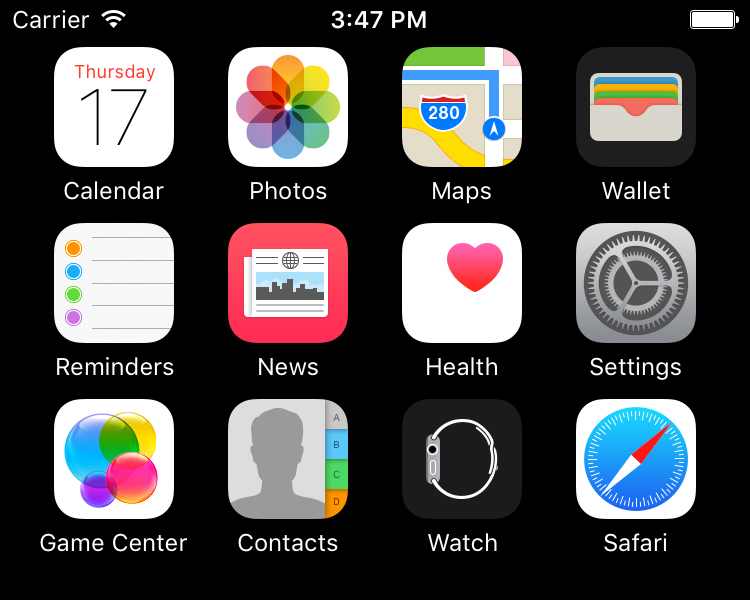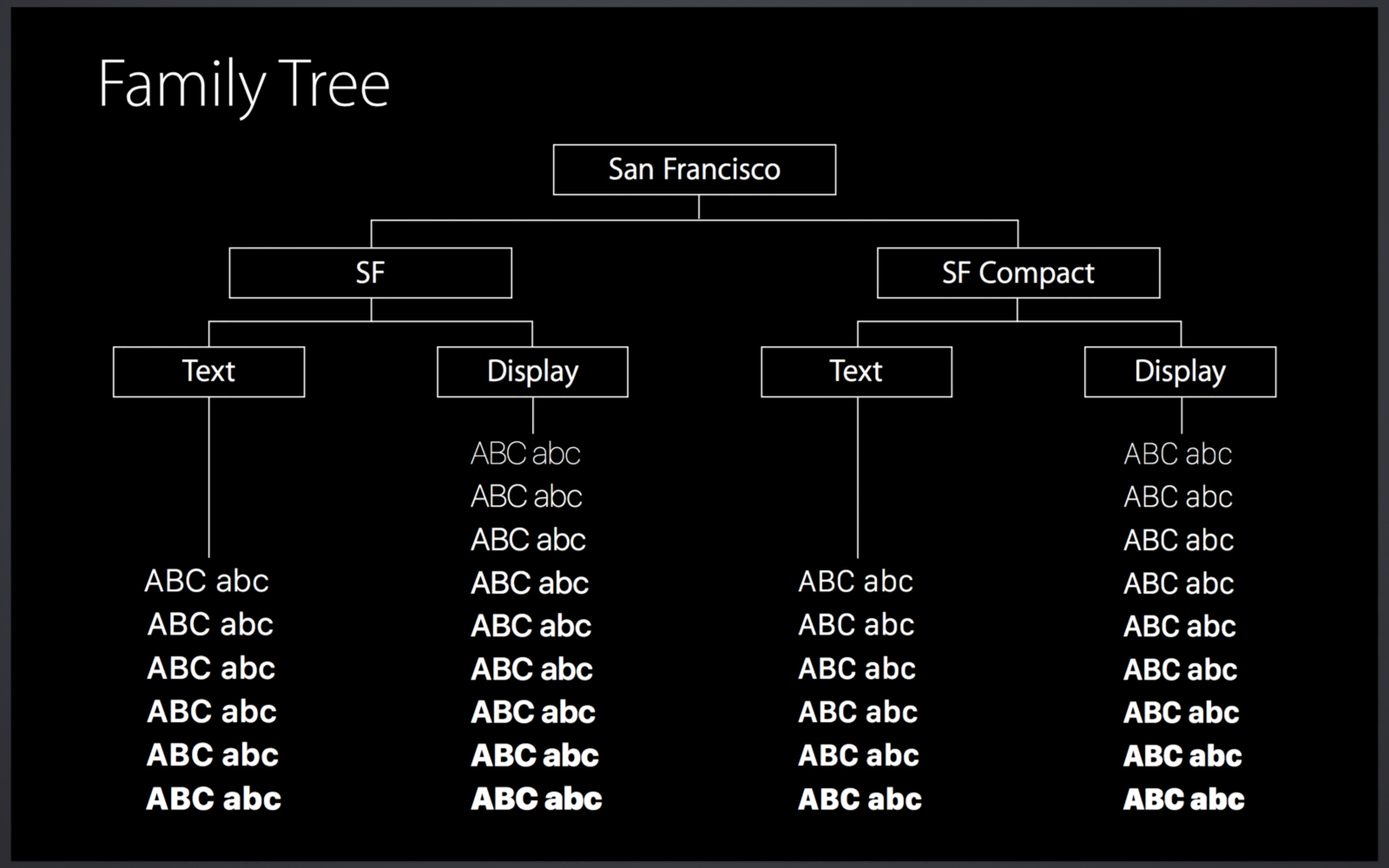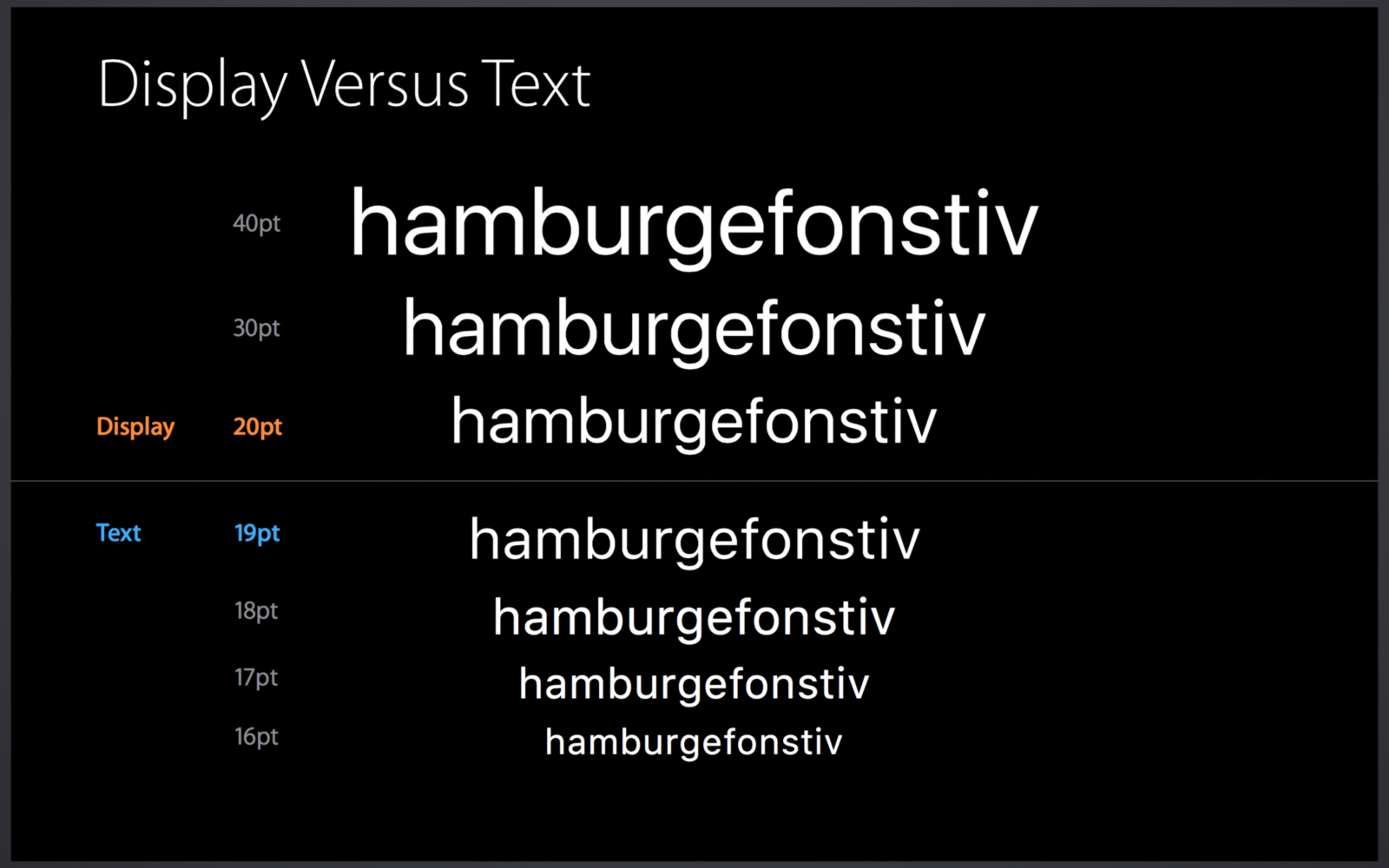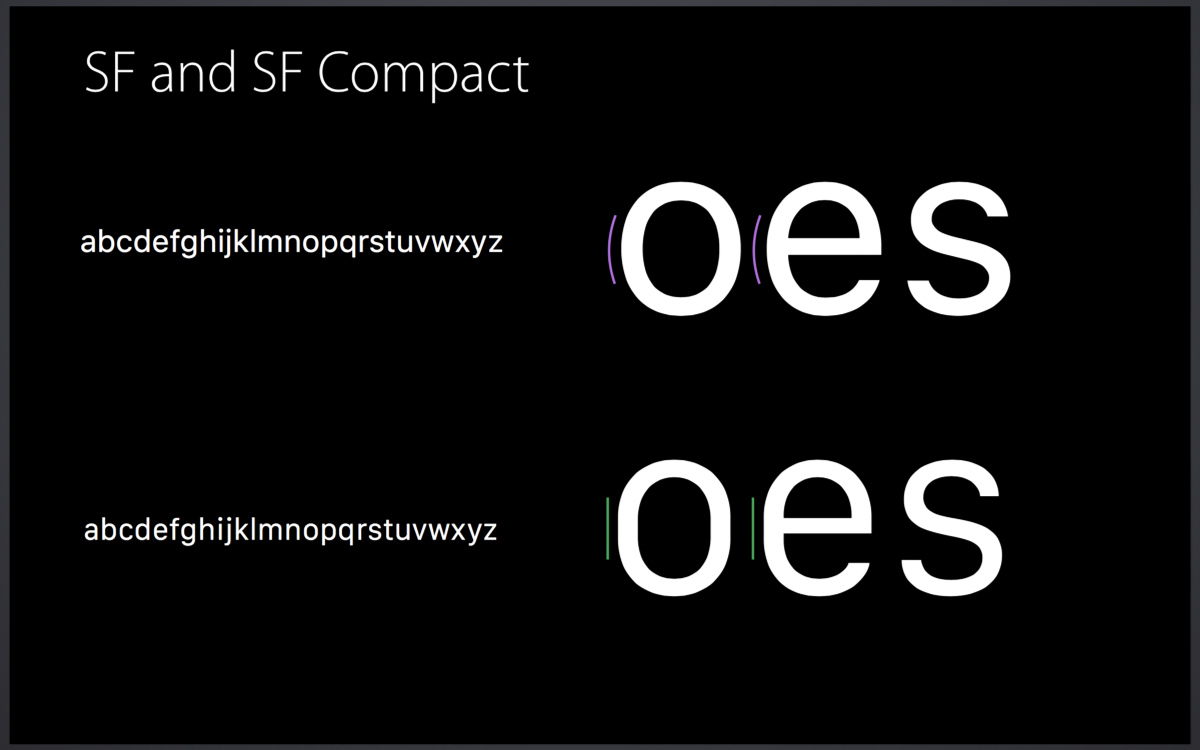
从iOS 9开始,苹果公司使用全新的San Francisco字体代替了之前的Helvetica Neue字体。目前这款全新的字体已经成为苹果各个产品平台的默认字体。
全新的San Francisco字体
Helvetica
Helvetica字体由一家瑞士公司于1957年设计,之后数字化。它历史悠久,甚至追溯到一个还没有电子设备的时代。自第一代iPhone开始,它就一直是iOS系统的默认字体,并且自"优胜美地"开始,苹果也将这款字体作为MacOS系统默认字体,替代之前的Lucida Grande。但究竟是什么原因让苹果公司决定淘汰它呢?
使用Helvetica字体的iOS界面
其实Helvetica字体有一个致命的缺陷是对小字号文字的支持欠佳,尤其是将它用在MacOS上面之后,这个问题变得尤为严重。很多用户尤其是设计师反馈说无法忍受这个字体的糟糕表现。
有人做了一张图片来对比Helvetica字体和其他几款字体的区别
从图中不难看出,Helvetica在小尺寸文本下的表现并不好,字母混合在一起,易读性很差。这对于即将发布智能手表的苹果公司来讲,无疑是一个致命问题,于是他们决定设计一款新的字体用于智能手表,San Francisco应运而生。但为什么苹果公司要将这款全新的字体用于iPhone和MacOS呢?要知道它们并不像Apple Watch那样,文字总是那么小。
San Francisco
事实上,但在iPhone / Apple Watch / Mac上所使用的并不是同一款字体,只是它们有一个统一的名称:San Francisco。在iPhone和Mac上使用的是一套名为SF的字体系列,而在Apple Watch上使用的却是SF Compact系列。下面的对比图你可以看到这两个字体系列之间的区别:
上图中能明显的看出SF Compact系列字体在各个字母之间有更大的间隙,这使得它即使是在Apple Watch这种小尺寸屏幕上也有很高的可读性。并且,这些字体都包含两个不同的子版本:Text版和Display版。Text版本用于较小的字号,而Display版则用于较大的字号,这便是苹果所谓的字体的"光学尺寸"。Text版字体在较小字号下有更大的间距和孔径,以提高文本的易读性。
另外值得一提的是,操作系统会根据不同的使用场景动态的切换不同的字体版本,在小文本上使用Text版本,其它使用Display版。用户无需关注到底该用什么字体,和一切都由系统自动确定。苹果对用户体验的专注和执着也由此可见一斑。